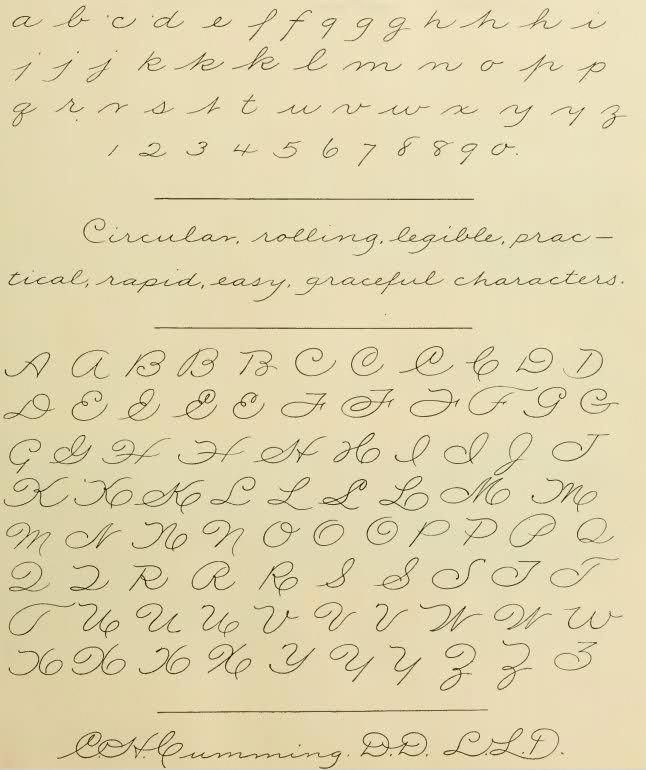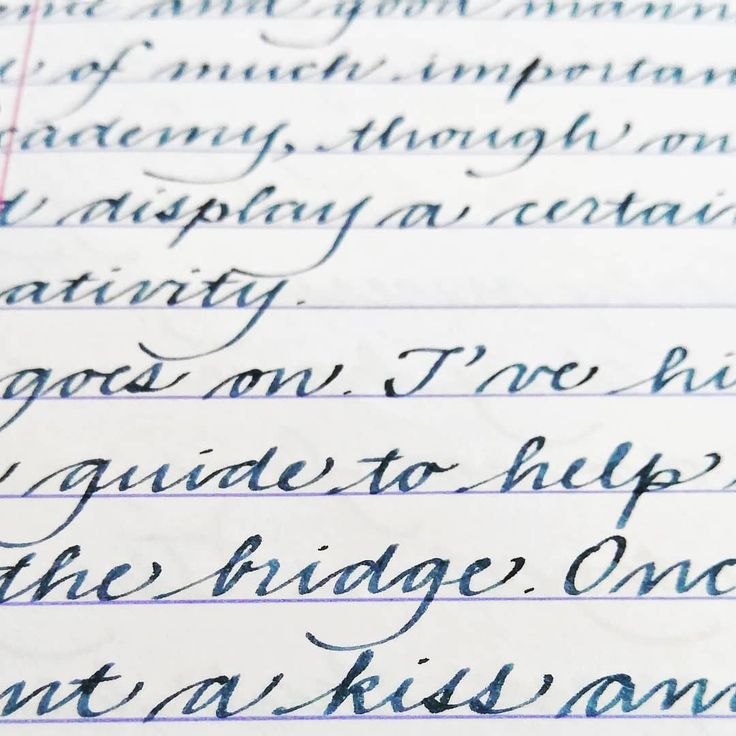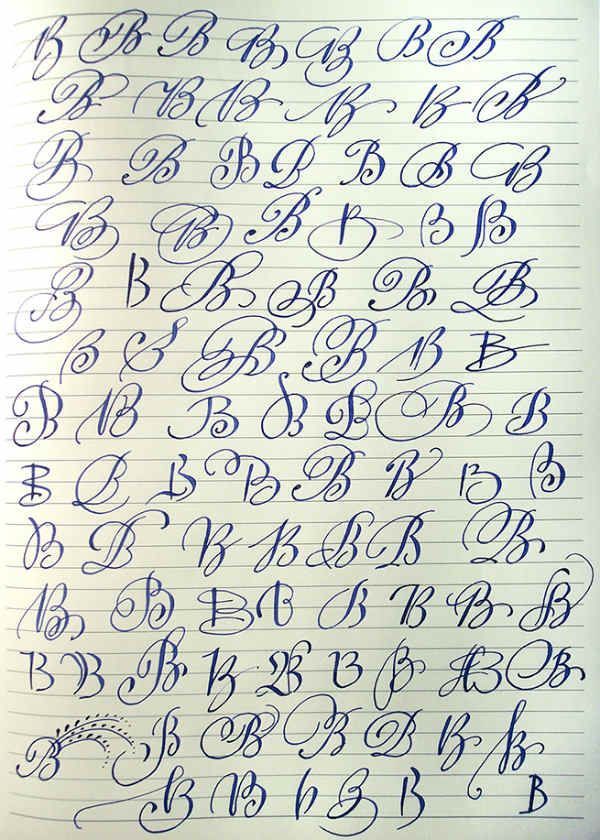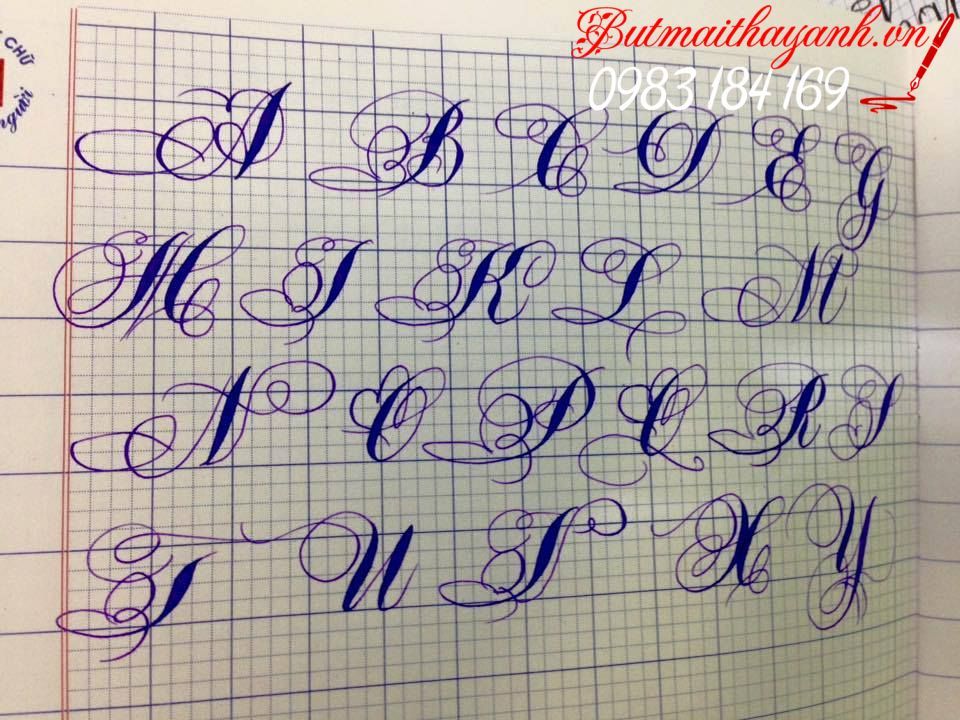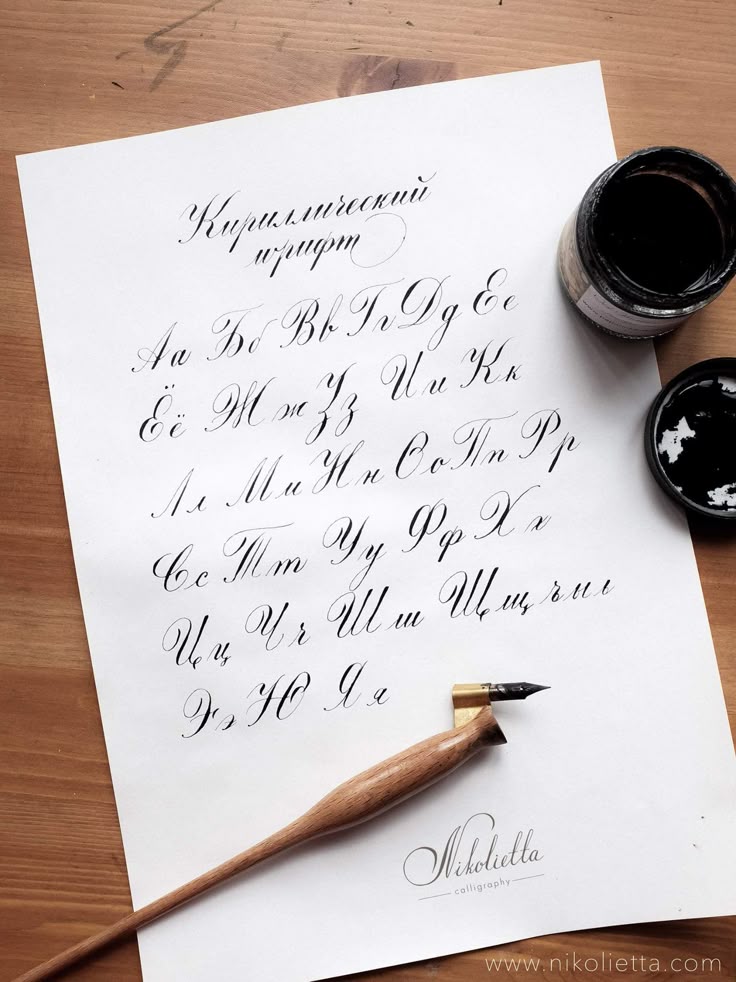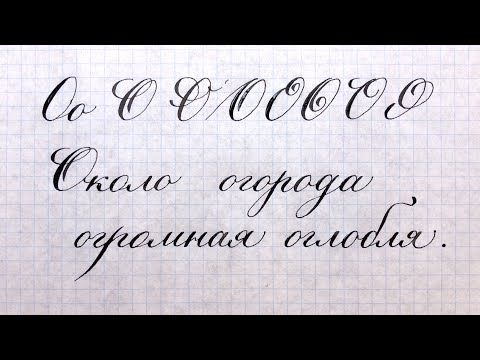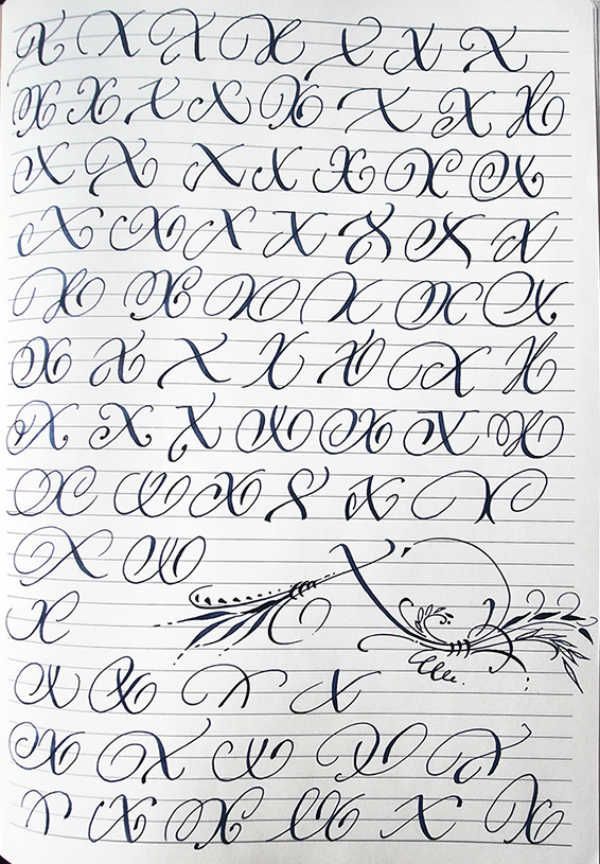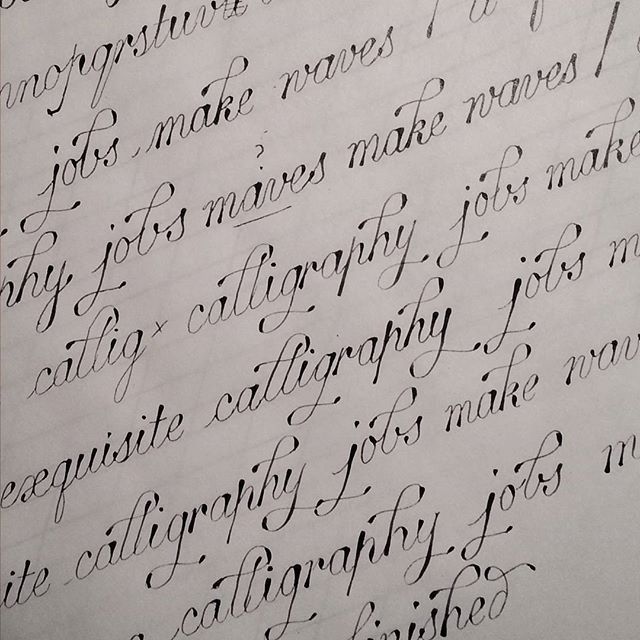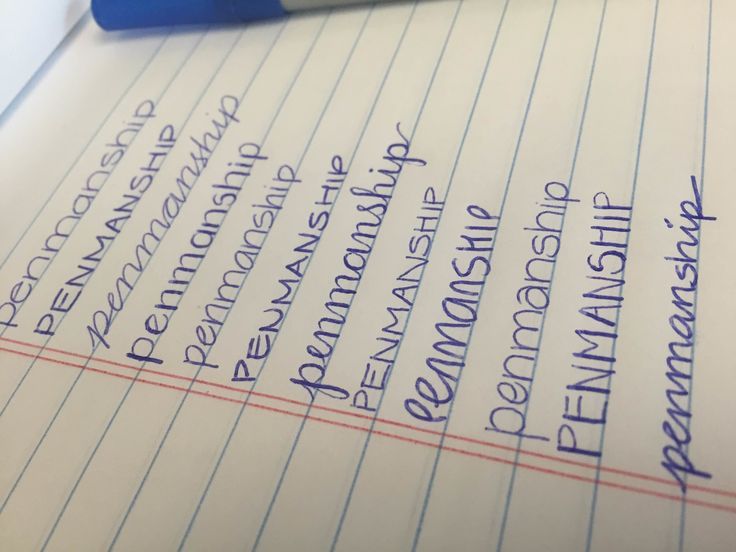
Изящный почерк
Красивое написание букв
Русский почерк
Английский почерк
Образцы почерка
Печатный почерк
Почерк с завитушками
Самый красивый почерк в мире
Фотография почерка восьмиклассницы из непальской школы Sainik Awasiya Mahavidyalaya разлетелась по сети интернет, словно вирус.
Все пользователи в один голос называют ее почерк самым красивым в мире.
Обладательницу столь красивого стиля рукописного письма зовут Милла Пракрити. Она учится в 8 классе. На своей странице в социальной сети ученица рассказывает о том, что умение красиво писать даже в современном мире необходимо. Оно помогает улучшить коммуникации между учениками и учителями. Так намного проще разобрать все предложения в тетради и педагогам будет легче проверять задания.
Девочка делится со своими подписчиками результатами проведенного исследования. Оно показало, что в 1992 г в школьных учреждениях уделяли намного больше внимания каллиграфическому написанию слов, нежели сейчас. Поэтому большинство детей и не утруждает себя писать красиво.
Титул самого красивого почерка девочка получила только благодаря мнению интернет-пользователей. Они считают, что столь красивые буквы должны стать основой нового шрифта в Microsoft.
Идеальность почерка Миллы оценило правительство Непала.
Девочка получила государственную награду как обладательница самого красивого стиля написания.
Каллиграфия
Искусство изящного письма называется каллиграфией. Сегодня в мире существует всего 15 направлений этой науки. Самыми яркими из них являются китайская каллиграфия и персидская вязь.
Нам самой близкой школой является кирилличная каллиграфия. Именно ее принципам в наших школах учат учеников младших классов. Все мы видели примеры написания букв по этому направлению – они часто публикуются на задней стороне тетрадей для письма и являются основой прописей для малышей.
Взрослый человек со временем также может пожелать улучшить свои навыки письма. Самым легким вариантом будет купить тетрадь с прописями и потренироваться.
Алфавит
Самые красивые почерки (100 картинок)
Почерк человека — это его визитная карточка. У кого-то красивый почерк с добавлением узоров, у кого-то совсем неаккуратный, размашистый, неровный.
Все мы разные и почерки у нас, конечно же, тоже отличаются. Если посмотреть на почерки поэтов или художников, сразу и не скажешь, что они принадлежат людям, создающим шедевры. Ведь, оказывается, у творческих людей как правило, очень плохой почерк, а у людей, относящихся к техническим сферам, почерк четкий, ровный и красивый. Итак, в данной подборке самые красивые почерки.
Правило написания
Красивые почерк
Буква ф по-разному написана
Прописные буквы
С написанием твердого знака
Буква В
Платон Воронько
Письмо на английском
Писание перьевой ручкой
Понятное написание
Письменные буквы
Сочинение
Стихотворение
Уважаемые господа
Добро и Зло
Английские слова
Перьевая ручка
Ноябрь,2015
Четверостишье
Красивое написание
Цветная записка
Печатные буквы
Сочинение
Письмо на иностранном языке
Красивый почерк
Старославянский язык
Газета
Буквы с завитушками
Диктант
Пропись
Секреты выработки красивого почерка
Научиться писать красиво лучше со школы.
Чтобы улучшить свой рукописный стиль, нужно:
- Перед упражнениями рекомендуется сделать небольшую зарядку для кисти руки, ведь она не привыкла писать много. Нужно сжимать и разжимать кулак, сделать круговые движения кистью, сгибать и разгибать пальцы.
- Тренироваться ежедневно, как минимум, по 20-30 минут.
- Купить качественную ручку и толстую бумагу, чтобы писать было удобно.
- Выбрать часть текста, которую нужно переписывать. Так со временем можно сравнить, есть ли результаты от усилий.
Эти несложные правила помогут улучшить почерк. Но нужно быть готовым к тому, что в первое время кисть руки будет сильно уставать.
Россияне пишут письма, открытки, стикеры и записки членам семьи, соседям и друзьям, списки покупок, рецепты, адреса, свои контактные данные, и многое другое!
Если вы умеете читать печатные русские буквы и планируете поехать в Россию, вы можете оказаться в невыгодном положении, так как встретите рукописные вывески и даже названия магазинов, станций и других важных вещей, напечатанных шрифтом, имитирующим почерк .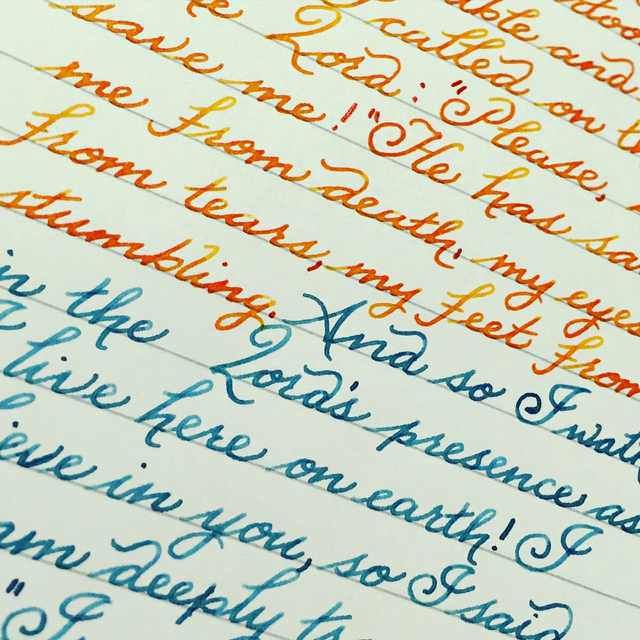
Девочка получила государственную награду как обладательница самого красивого стиля написания.